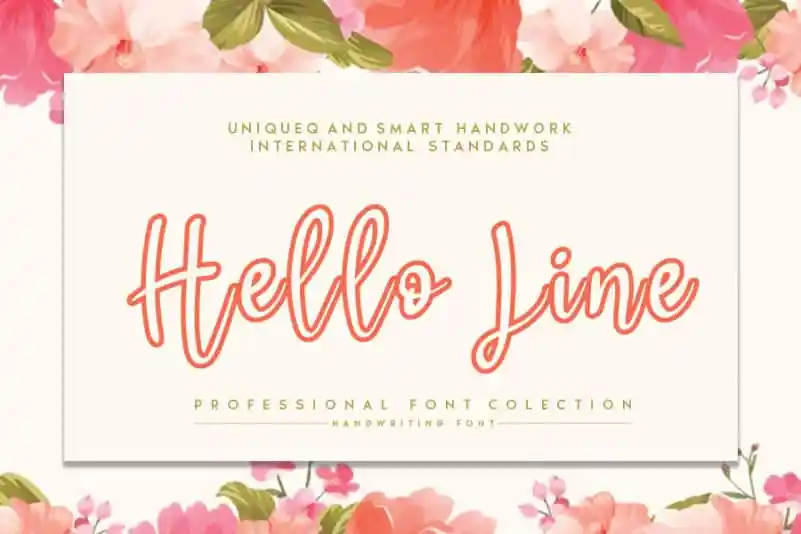
Hello Line Script Font – Download Grátis
Descubra a Hello Line Script Font, uma elegante e fluida fonte de display ideal para personalizar seu layout com estilo único. Essencialmente versátil, essa fonte não apenas enriquece sua tipografia convencional, mas também adiciona um toque sofisticado e moderno a qualquer projeto. Adaptable para uma variedade de aplicativos, seja em cartões de casamento sofisticados ou estilosas obras de arte de registro; em postagens do Instagram capturando atenção ou artes de mídia social intrigantes; até mesmo na criação de designs de redes sociais inspiradores e únicos. Com a Hello Line Script Font, você pode experimentar um novo nível de criatividade e personalização. Escolha a fonte perfeita para seus projetos digitais, seja no design de sites, em gráficos publicitários ou até mesmo nos designs para impressão digital, tornando cada projeto único. Seja qual for o seu objetivo, a Hello Line Script Font tem uma solução ideal que vai destacar seu trabalho.